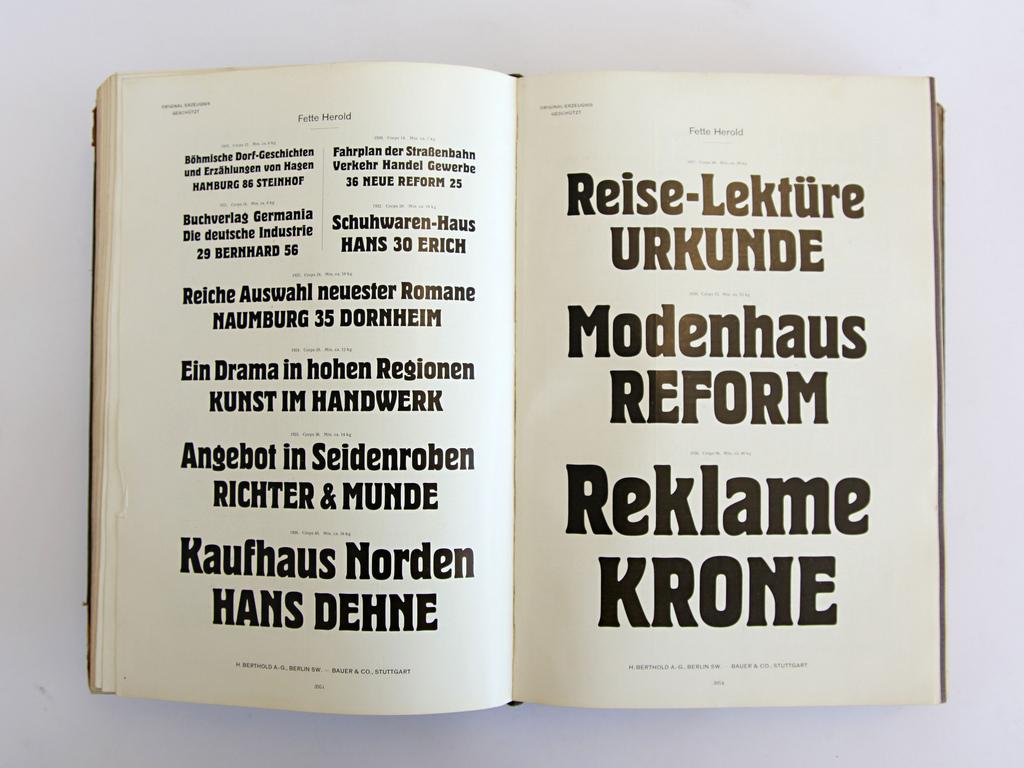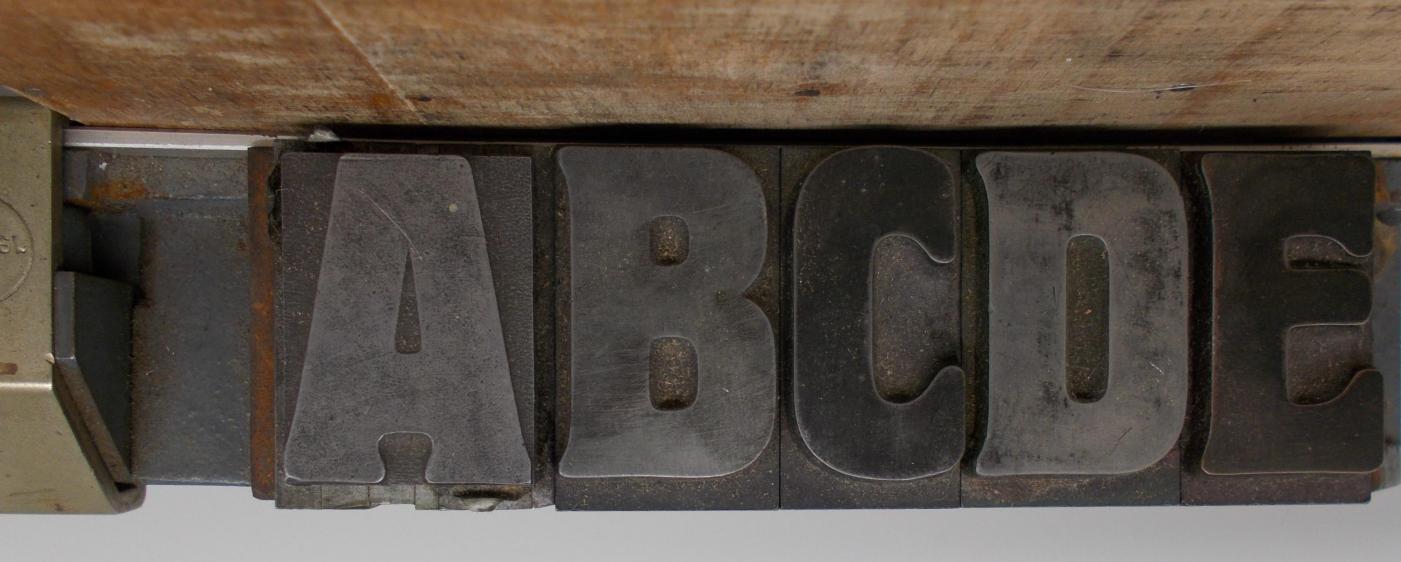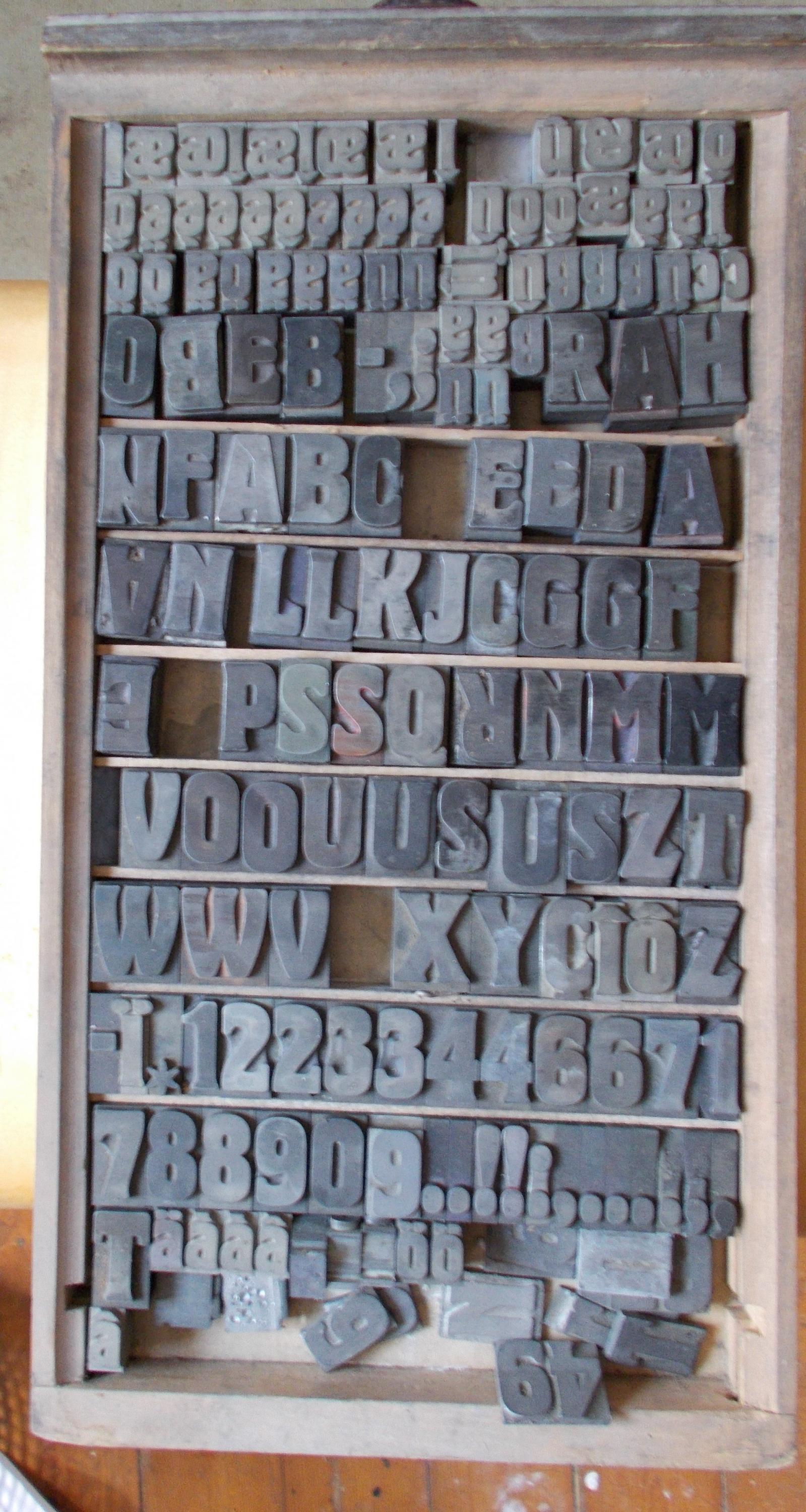
Steht 36p am Kasten? Wenn da eine 3 steht, sind es eher drei Konkordanz, nicht Cicero. Die Versalien haben vielleicht zwei, die Unterlänge dazu, das müßten dann drei Konkordanz sein. Wenn ich das mal so schätze in Proportion zum Winkelhaken.
Die Stahl (Erstguß 1939) sieht anders aus: http://bleisatzmagazin-rheinland.de/shop/antiqua-varianten/stahl-24p.html
Die Versalien haben vielleicht zwei, die Unterlänge dazu, das müßten dann drei Konkordanz sein.
Mal davon abgesehen, dass die Beschriftung des Setzkastens wahrscheinlich nicht stimmt, ist diese Schrift ja offensichtlich nicht auf der Normalschriftlinie, da ist also kaum Platz für so eine Unterlänge ist.
3 Konkordanz? Das sind doch 144 Punkte? Das ist doch dann schon eine ausgewachsene Plakatschrift bei der die Buchstaben der abgebildetebn Schrift gut 5cm hoch wären?
36p = Cano = 3 Cicero, diese Rechnung würde ja stimmen, Die frage ist nur, passt das zu deiner Schrift. Wie hoch ist den dein Kegel?
Messe das einfach mal mit nem Messschieber, und teile die gemessenen Millimeter durch 0,376.
Und hast du nur Versalien, oder sind da auch die Gemeinen dabei?
Ja, 3 Konkordanz sind 12 Cicero sind 144 Punkt. Wenn die Unterlänge so kurz ist, daß sie auf denselben Kegel wie die Buchstaben ohne Unterlänge paßt, beträgt der Schriftgrad 2 Konkordanz. Diese Größenangaben sind bei Holzschriften nur ungefähre. Ich hab ziemlich krumme Kegelgrößen im Kasten, z.B. 14c4p für einen Buchstaben mit Unterlänge. Oder auch Schriften, bei denen es unterschiedliche Kegel bei den Buchstaben mit Unterlängen gibt. Das Kegelmessen gibt einen ungefähren Wert, der typografische Punkt spielt da keine wesentliche Rolle. Wir haben früher anders gearbeitet, bei diesen Dimensionen war alles so ungefähr.
Ich habe mal 2  4Cicero Ausschluss dazugelegt: passt. Also 8 Cicero (96 p)
Die Gemeinen sind kleiner: 56 p
Wie zu sehen sind am unteren Bildrand einige Lettern  ohne Kegel zu sehen. Ich denke diese wurden auf entprechende Unterlagen (Holz) genagelt.